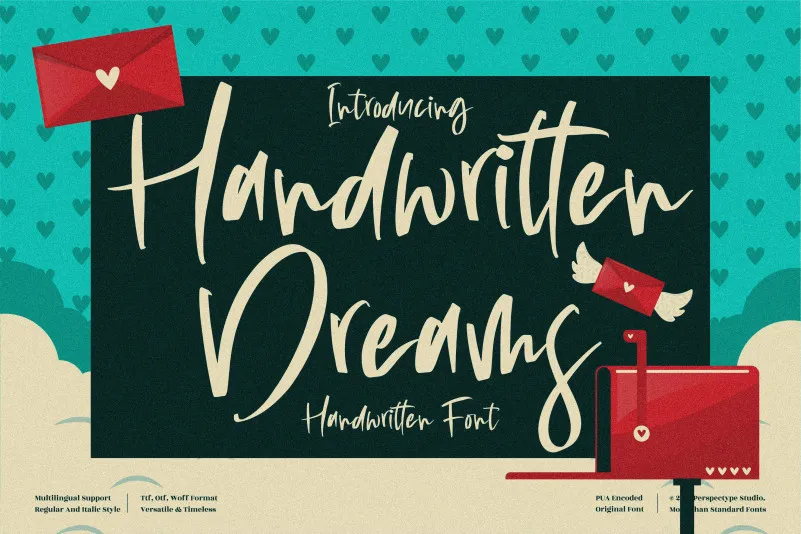
Handwritten Dreams Font – Download Grátis
Esta é uma elegante e fluida fonte de script. Desejosa e descontraída, esta foi criada para vários designs que exigem um toque casual e informal. Adicione-a confiante a seus projetos, e amará os resultados obtidos. Perspectype é o designer desta maravilhosa fonte brush, ideal para personalizar qualquer projeto de design gráfico com uma sensação única e encantadora.